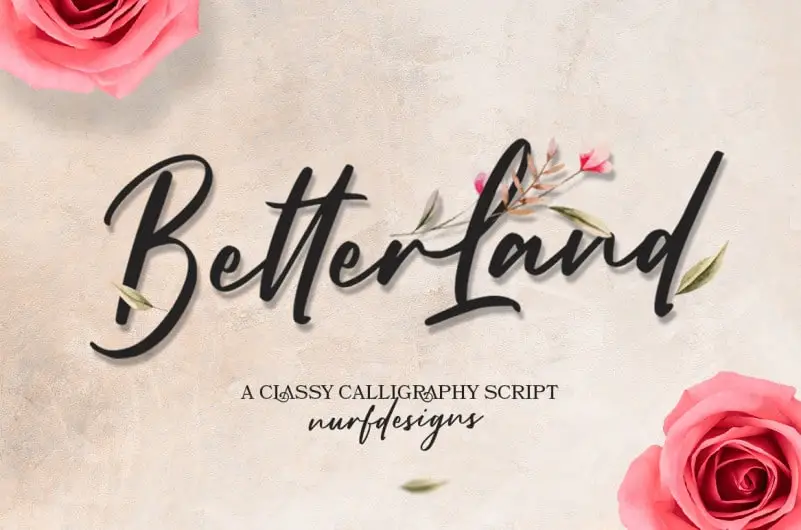
Better Land Script Font
Melhor Terra Script Font é uma fonte escrita a mão com um estilo clássico e nostálgico. Ideal para qualquer projeto que precise de um toque sofisticado, seja ele logomarcas, identidades corporativas, projetos de redes sociais ou até DIY criativos. Esta fonte não apenas adicionará um charme único a seus trabalhos gráficos, mas também permitirá que você faça um impacto inegável em qualquer projeto onde ela for usada. Seja para dar vida à sua marca online ou para personalizar itens de casa com estilo, Melhor Terra Script Font é uma escolha inteligente e elegante para todos os criadores de conteúdo digitais.